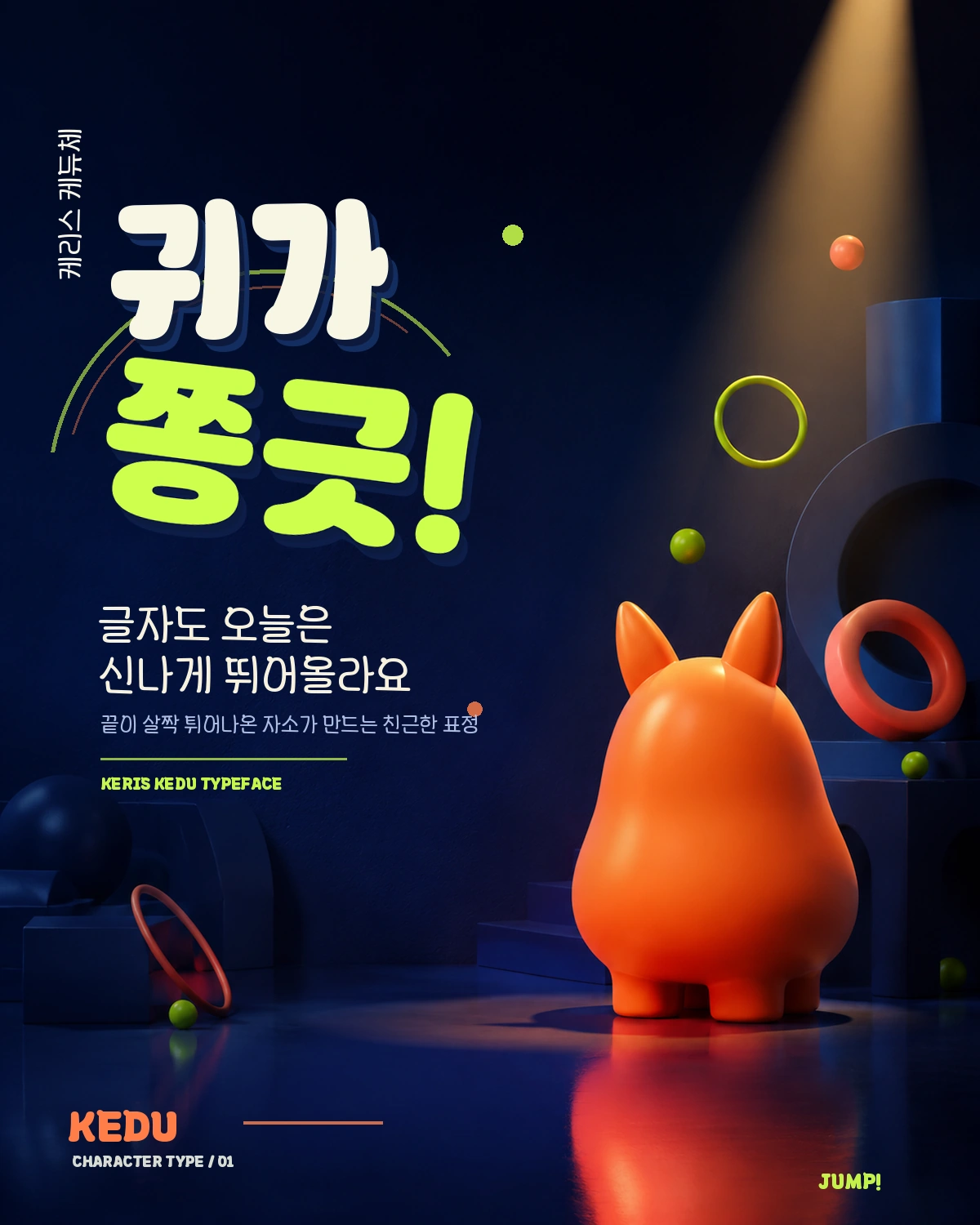
케리스 케듀체 — Keris에서 배포하는 무료 폰트입니다. 기관 캐릭터 케듀의 쫑긋 튀어나온 형태를 자소에 옮긴, 통통하고 친근한 장식용 서체
한국교육학술정보원이 자기 기관을 상징하는 서체로 만들어 2025년 말에 공개했고 투게더그룹이 제작했습니다. 학교 안심폰트 공모작이 아니라 기관 아이덴티티 서체라는 점이 다릅니다.
모티브가 캐릭터에 직결됩니다. 기관 설명 그대로, 케리스의 캐릭터 케듀의 모습을 나타낸 서체로 케듀의 쫑긋 튀어나온 귀와 통통한 배와 발을 글자에 담았습니다. 캐릭터의 신체 부위가 자소의 형태로 옮겨진 셈이라 글자를 보면 어느 부분이 무엇인지 짐작이 갑니다.